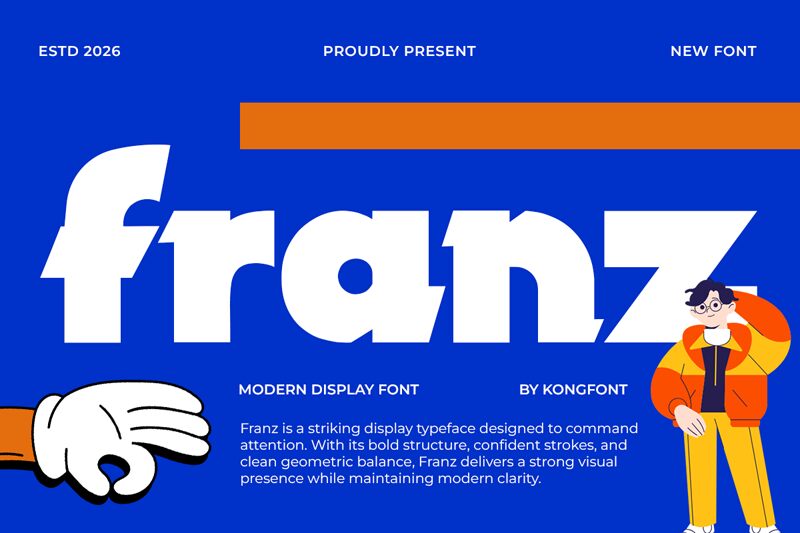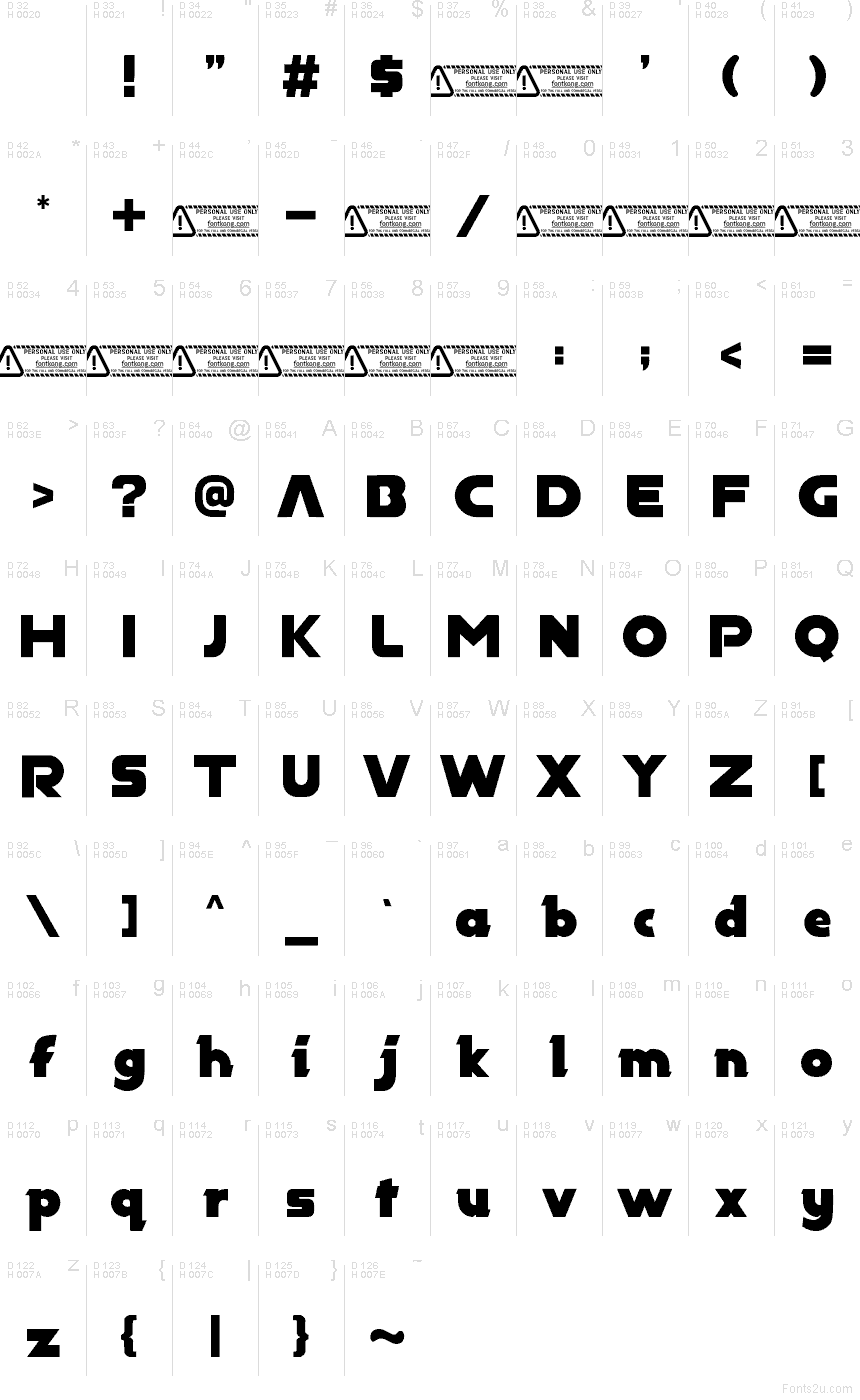
Il font Franz di Kong Font colpisce per i suoi caratteri spessi e squadrati, che danno l'impressione di essere stati stampati nell'acciaio. È un font sans serif audace, il cui ritmo massiccio rimane leggibile anche quando si ingrandiscono i caratteri per dominare la pagina.
Usa Franz su poster, logotipi sportivi, grafica streetwear, copertine di album, etichette, miniature di YouTube, volantini di eventi o insegne d'impatto per dare subito peso ai tuoi titoli. Mantieni la spaziatura leggermente aperta per dare respiro e abbinala a un sans serif neutro e sottile per i sottotitoli, lasciando che questo font gratuito si prenda la scena.